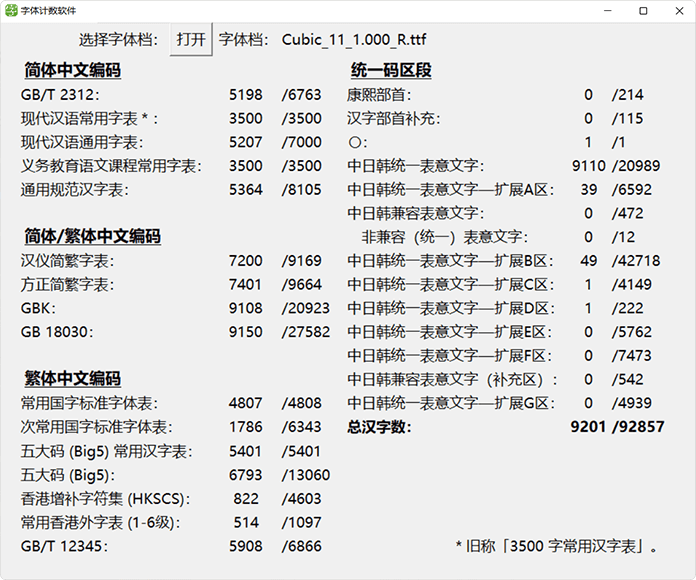
俐方体11号是基于M⁺ gothic 12r衍生的开源繁体中文点阵字型,可用于像素风格的游戏以及美术当中。
字形调整
本字型以日文字型 M⁺ gothic 12r 为基础替繁体中文进行修改与扩充,其中包括适用繁体中文的标点符号以及较符合台湾地区习惯的字形等。
收录字数
- 常用国字标准字体 4808 字。
- Big5 第一字面 5401 字。
- IICore 台湾常用字 T1A、T2A 及部分 T2B。
- 台客闽粤字。
- 注音符号。
- GB 2312 Level-1。
- 通用规范汉字表 一级。
- 元素週期表之所有元素字符。
Ver 1.100(2023/10/31)
- 新增字符「呗」、「鲲」、「闵」、「髅」、「啬」、「诙」、「燁」、「Œ」、「œ」。
- 修正字符「ß」長得像 beta(β) 的問題。
Ver 1.010(2022/02/22)
- 修正「与熵羥羧羰萘蒽虬虯㗾𨧀𨨏𨭆𨭎鿫鿬」字符偏移的問題。
- 新增字符「捋、跩、踅」。
Ver 1.000(2022/01/23)
- 俐方体11号正式发布